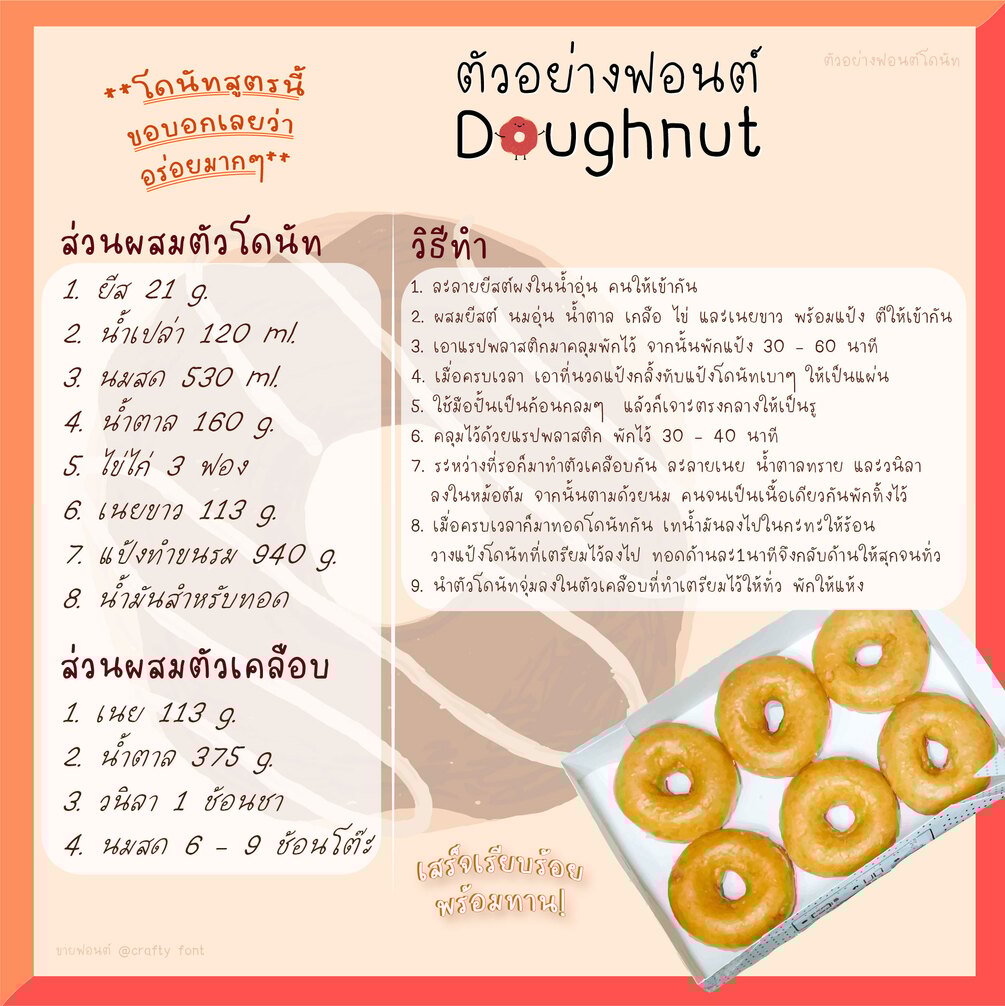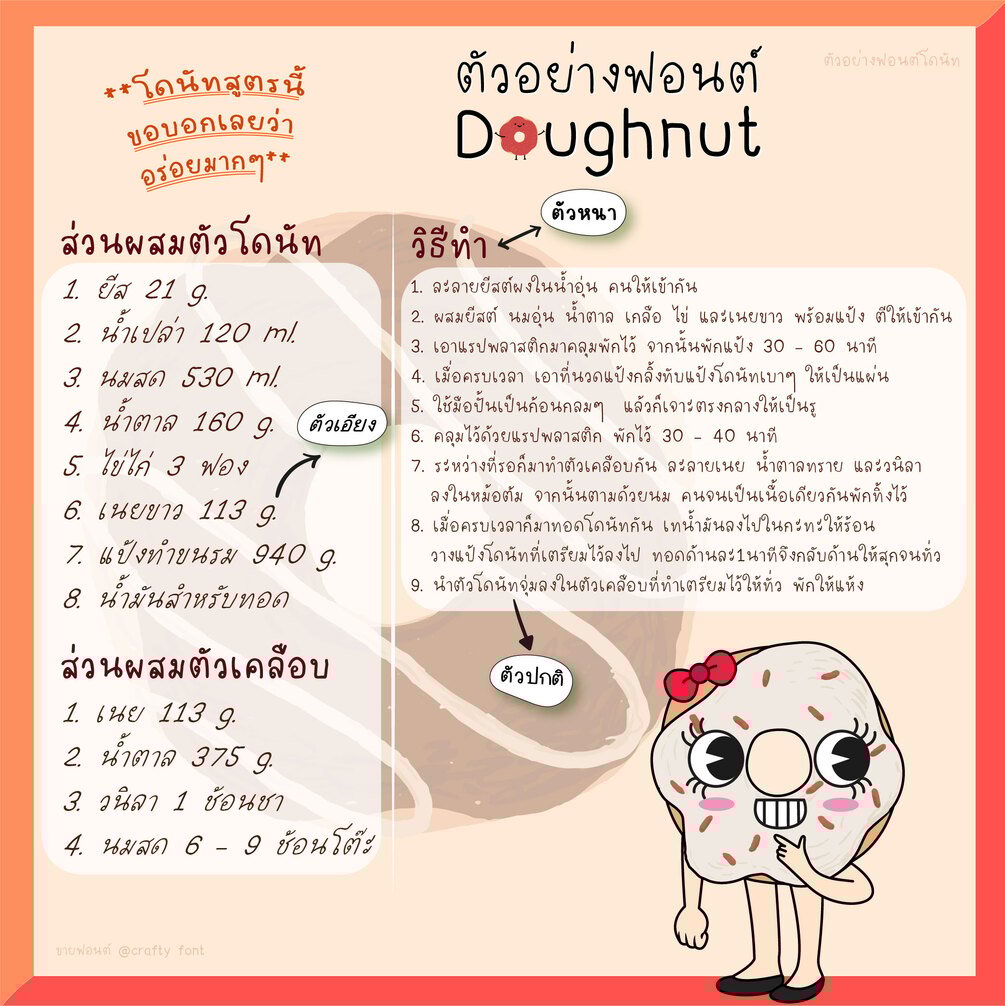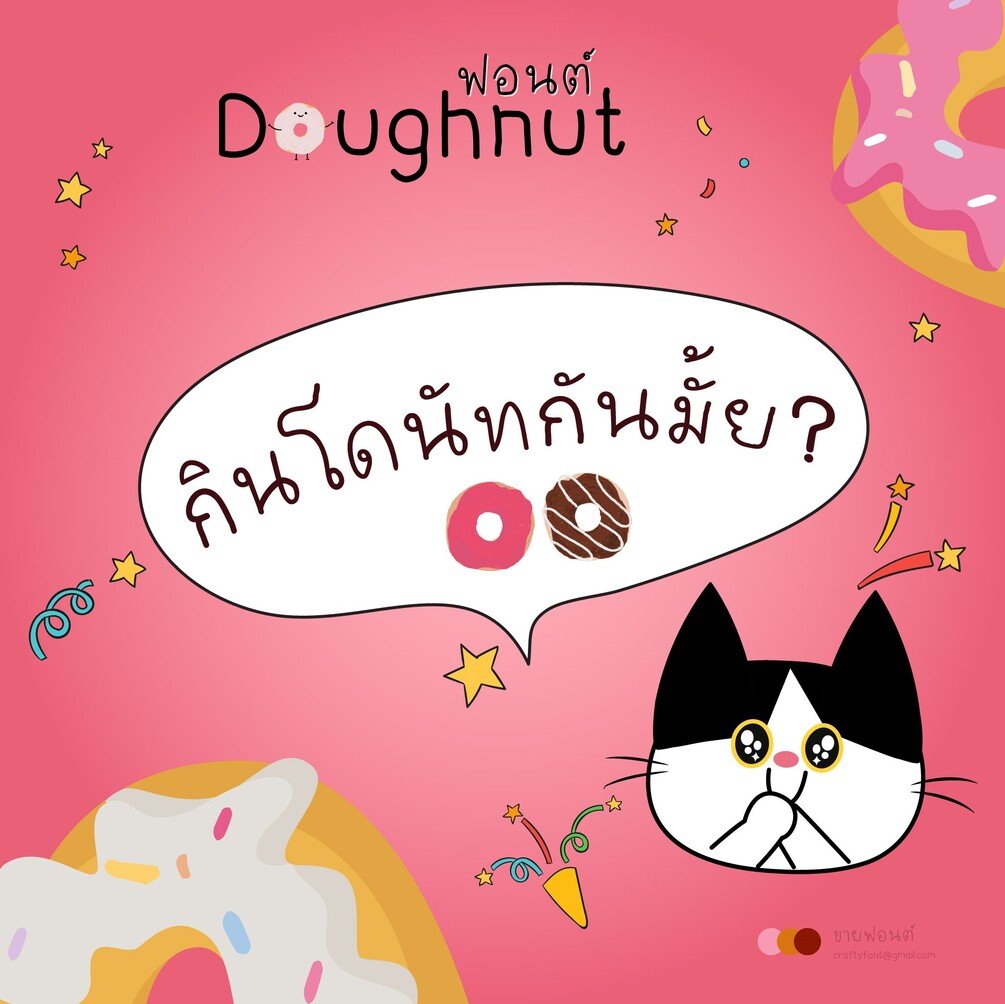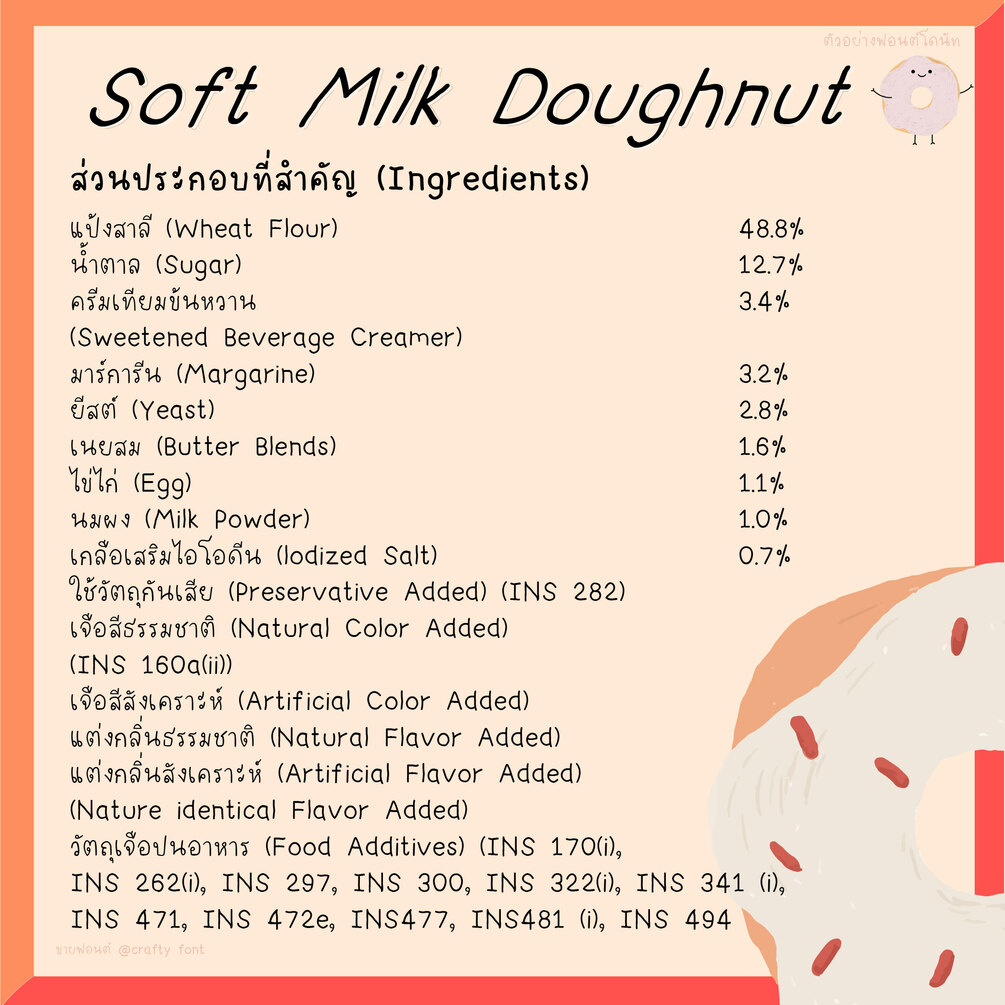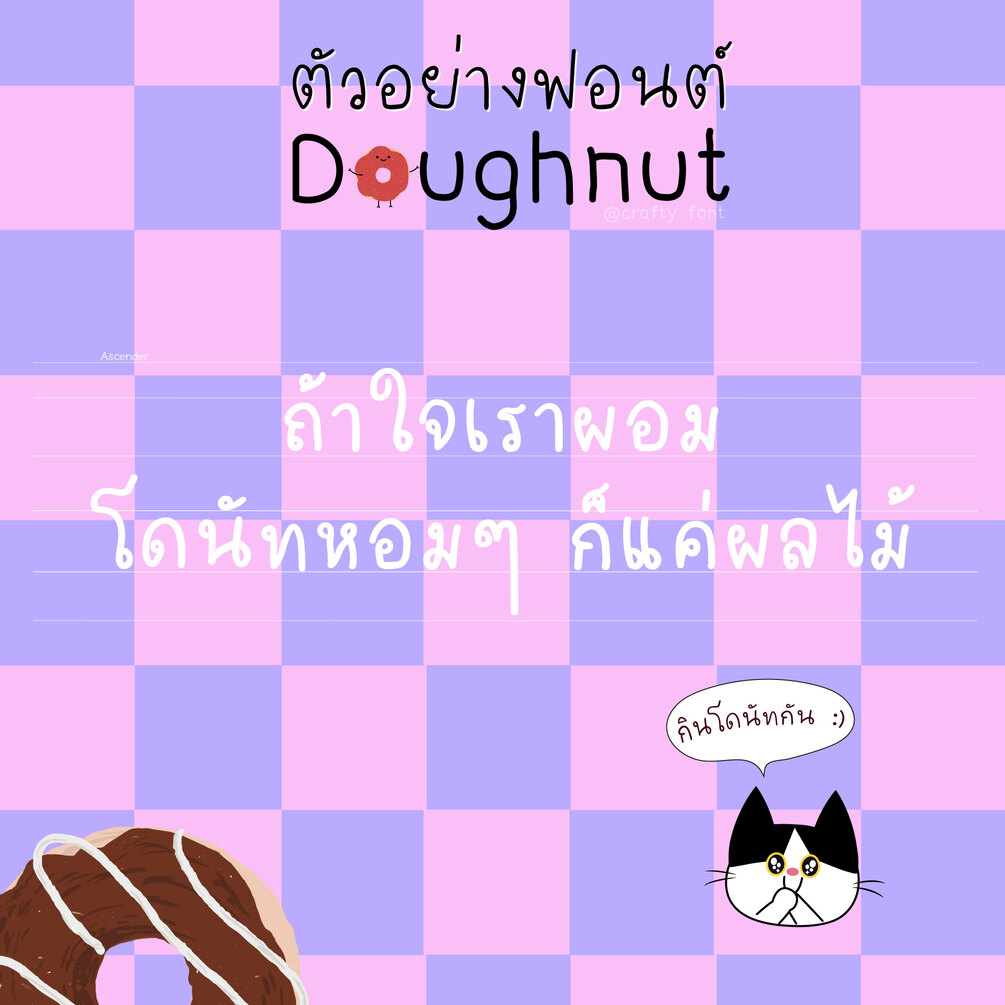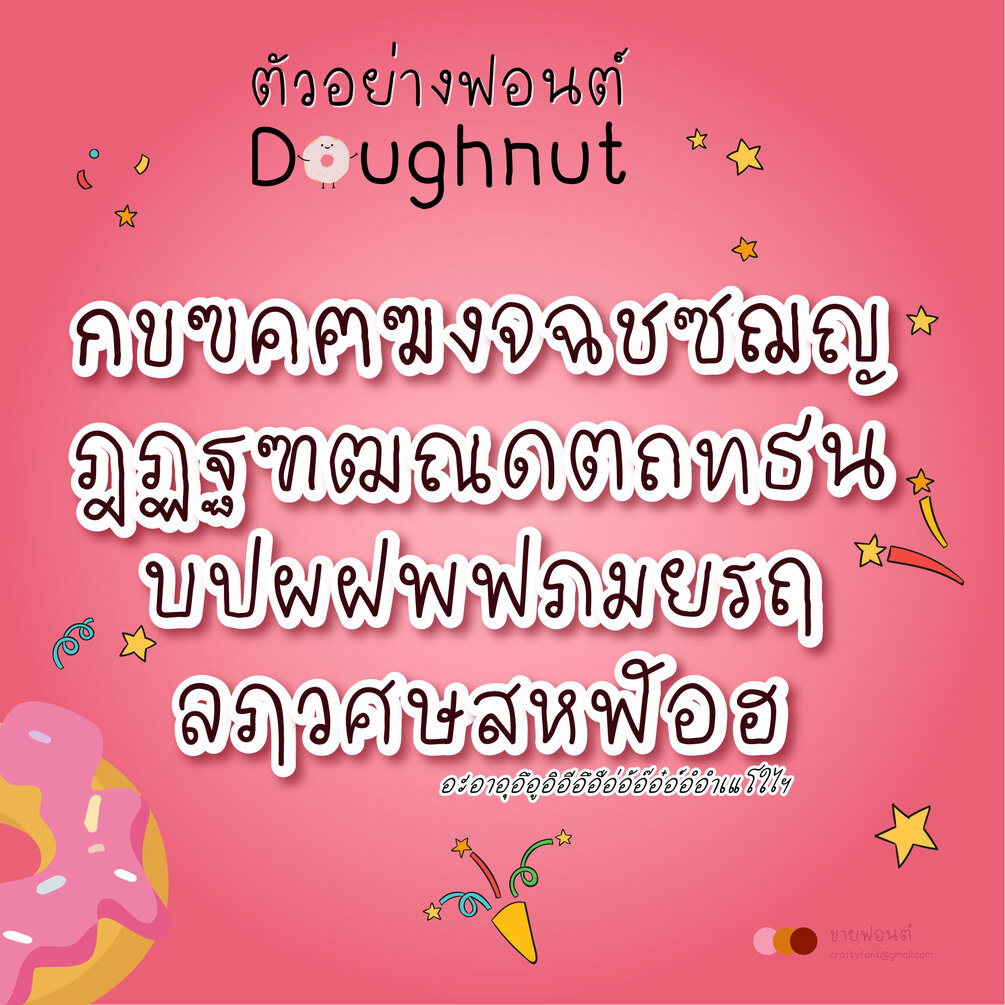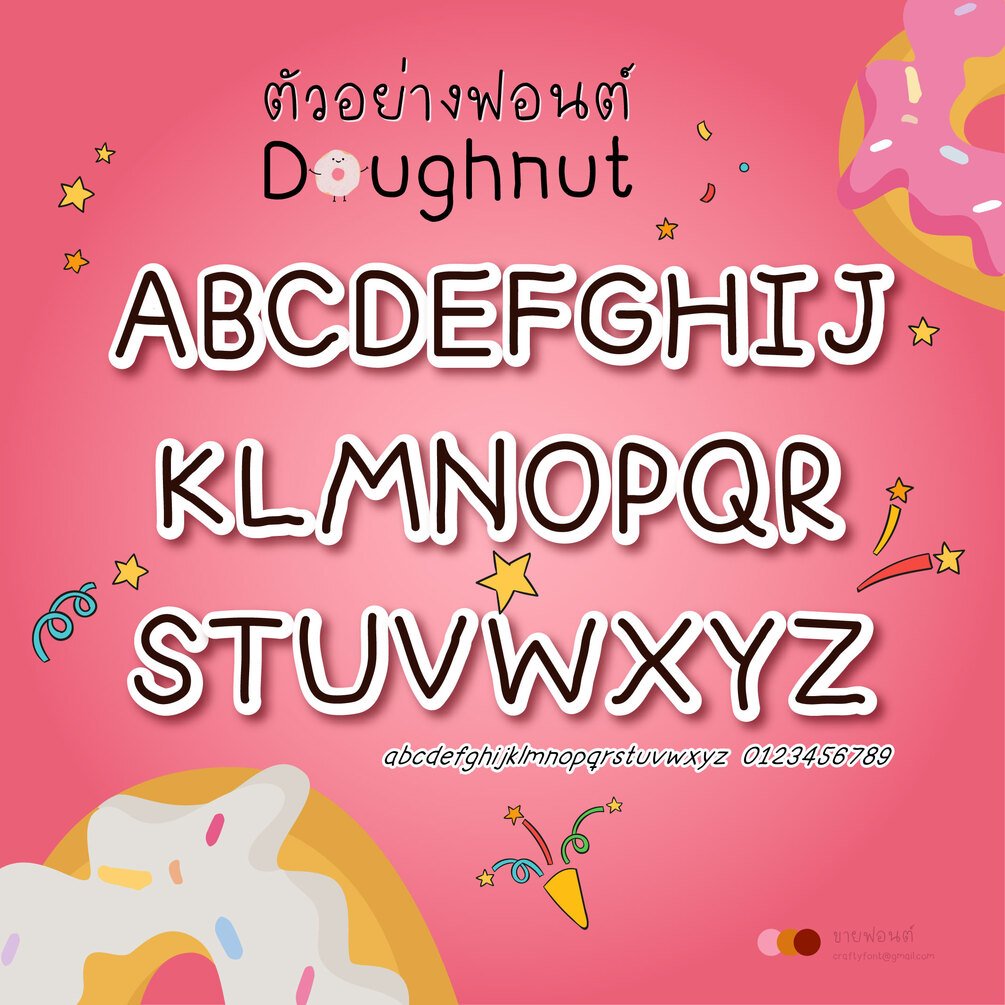
Doughnut Font (ฟอนต์โดนัท)
มาเพิ่มน้ำตาลในเลือดด้วยฟอนต์โดนัท ฟอนต์นี้ ไม่มีไขมันทรานส์นะ!! 🍩
เส้นของน้องจะขยุกขยิก หยึกหยักแบบไม่ตั้งเขียน เขียนส่งๆ (ว่าซั่น)
ฟอนต์มีทั้งภาษาไทยและภาษาอังกฤษเลยนะคะ บวกลบคูณหารมีให้ใช้ครบ ฝากไว้ในอ้อมอกอ้อมใจพี่จ๋าด้วยนะจ๊ะ 🙏🏻